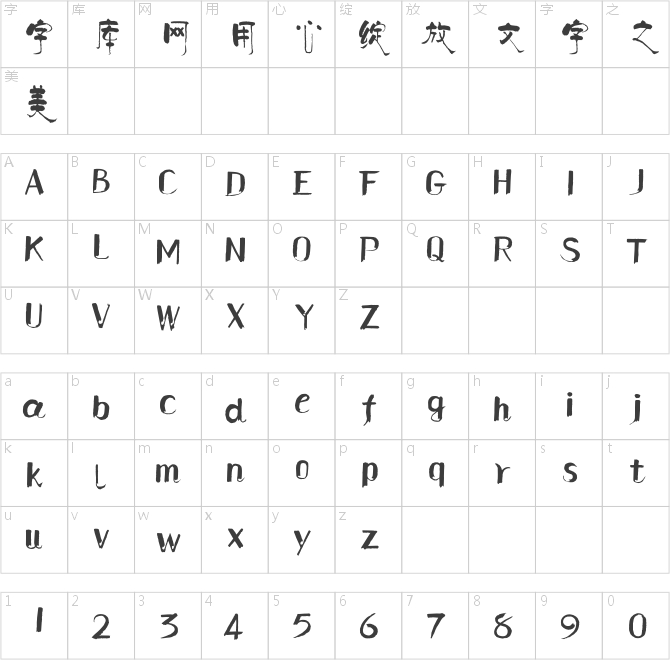
字體名稱: 迷你簡(jiǎn)柏青
迷你簡(jiǎn)柏青
迷你簡(jiǎn)柏青字體字庫(kù)是一款讓人賞心悅目、百看不厭的中文字體,適合各類廣告和產(chǎn)品包裝設(shè)計(jì)應(yīng)用,字體大小6.66MB,格式為ttf字體,上傳用戶是瓜皮,作者/版權(quán)方為疑似偽造